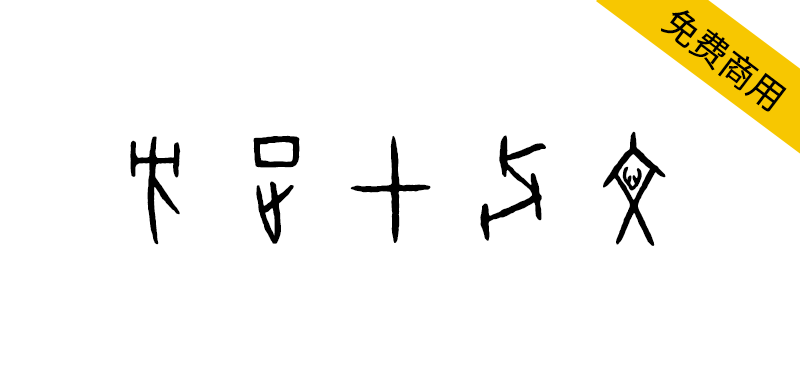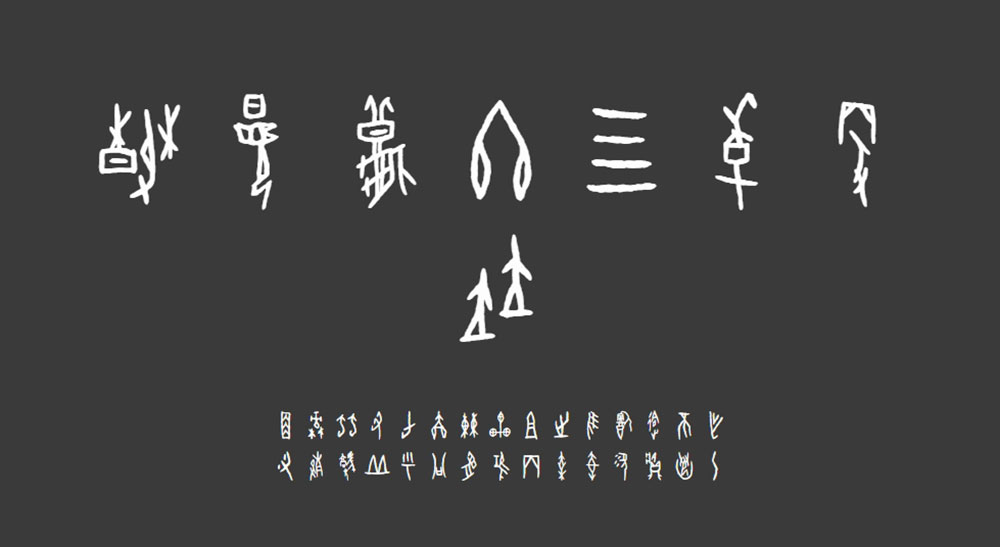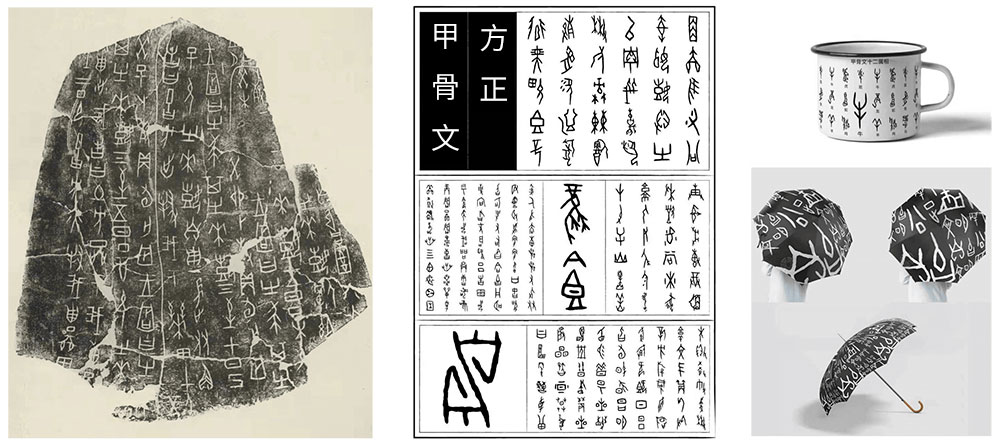
方正甲骨文字库为繁体字库,共收入1430字。字形以原拓为基础,为全套字库视觉统一起见,部分字的笔画粗细略有调整。字形风格的选择以典型宾组类(宾组二类)为主,其他组类次之,在设计选择时尽量贴近典型宾组类风格。
关于甲骨文:甲骨文,是我国最早的文字(约公元前1500——公元前1100)。甲骨文象形的意味最为明显,是以表形为主、表意为辅的文字。甲骨文是中国文字之根,中国书法之源,篆书之祖。甲骨文 指刻写在龟甲、兽骨上的文字。主要发现于河南安阳小屯村一带的殷墟,是商代后期王室和贵族用于占卜和记事的文书,又称契文、甲骨刻辞、卜辞等。所发现的殷墟带字甲骨的数量已有16万片之多,是目前已知中国最早的成体系的文字,主要记载了殷商社会的历史和文化。殷墟所出土的是商王盘庚迁殷至纣亡近二百五十年间的遗物,它既是研究商代文化的宝贵文献。也是我国最早的文字实证。我们今天所使用的汉字和甲骨文一脉相承,中国文字发展的历史长河从来就没有中断过,很多字在甲骨文中就已经定型了,它们的音、形、义有着密切的“血缘”关系。 从甲骨文发现到现在已逾一百二十余年,甲骨文的国际影响力和文化意义日益彰显。
字体特征:甲骨文字库收录字形均在相对公认的已释读的甲骨文范围之内;字形主要以殷墟卜辞原拓和部分周原甲骨文为基础;以典型宾组类为主要字体风格;其字形结体对称而稳定,其线条遒劲坚实、挺拔爽利,曲直粗细均备,笔画多方折。甲骨文字库还原了文字的象形,生动而有趣,又充满了历史的厚重感。
设计师:陈宇